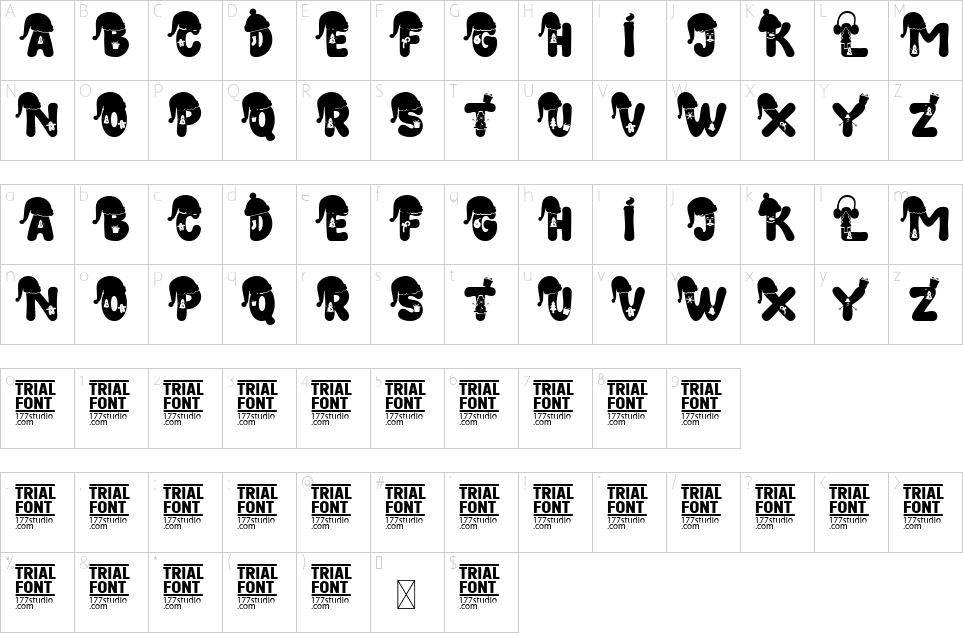
A fonte Greatness Christmas é uma bela escolha para aqueles que desejam adicionar um toque especial à sua decoração natalina ou design durante a época do ano mais bonita. Ela foi criada por 177studio.com e já foi baixada pelo número impressionante de 381 usuários, demonstrando seu valor e popularidade entre os amantes da fonte para eventos festivos. Com sua elegância e suavidade, Greatness Christmas combina perfeitamente com o espírito natalino, tornando-a um dos recursos gráficos indispensáveis para suas anotações de Natal ou seus projetos digitais. Baixe agora a font Greatness Christmas e transforme qualquer projeto em uma verdadeira obra prima desta data especial.